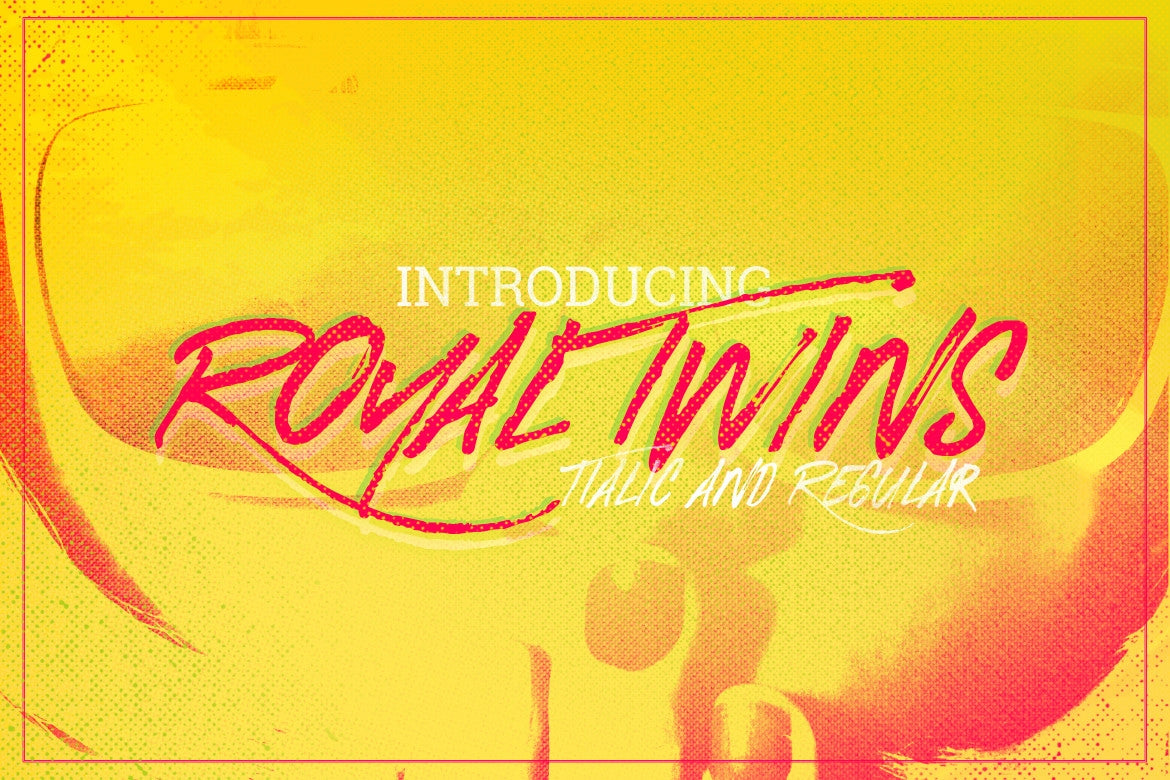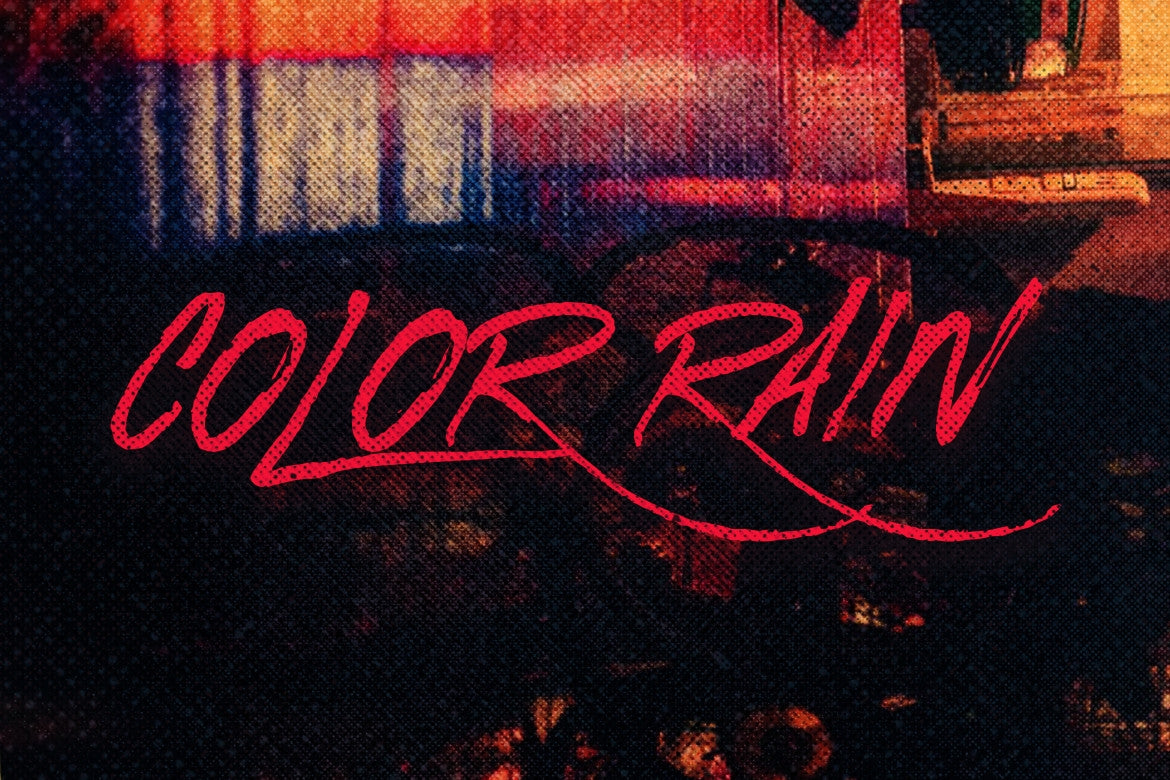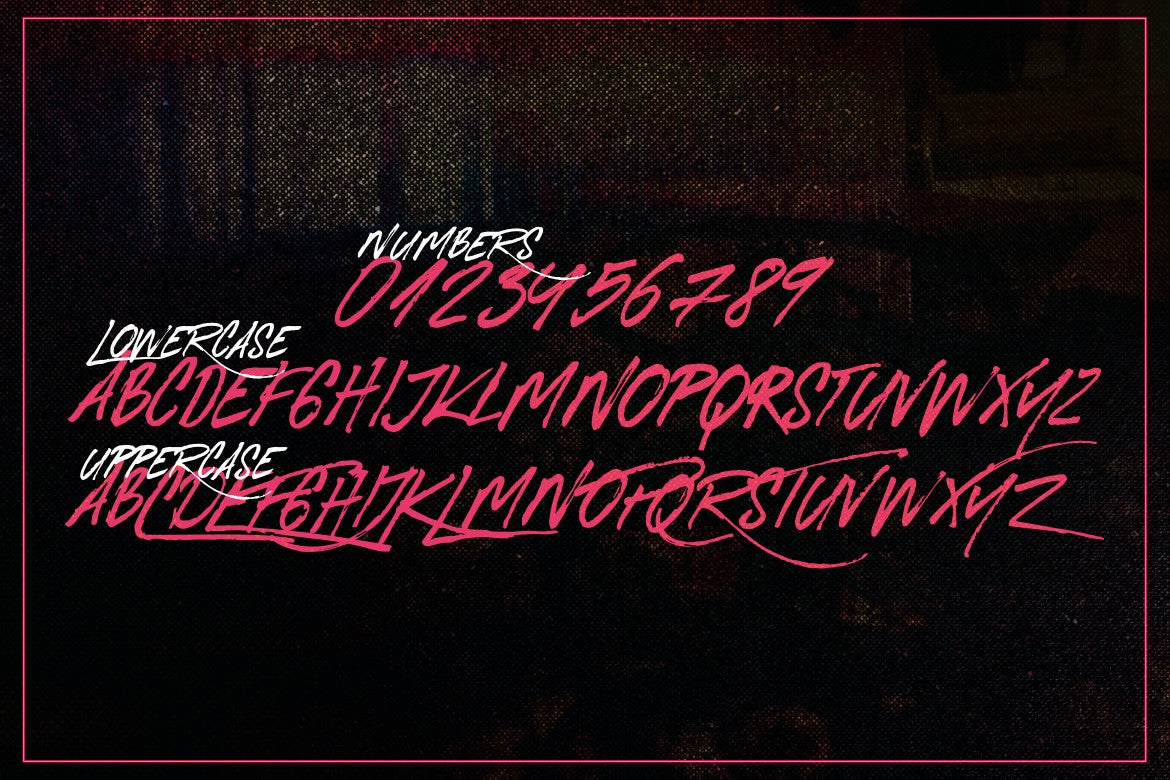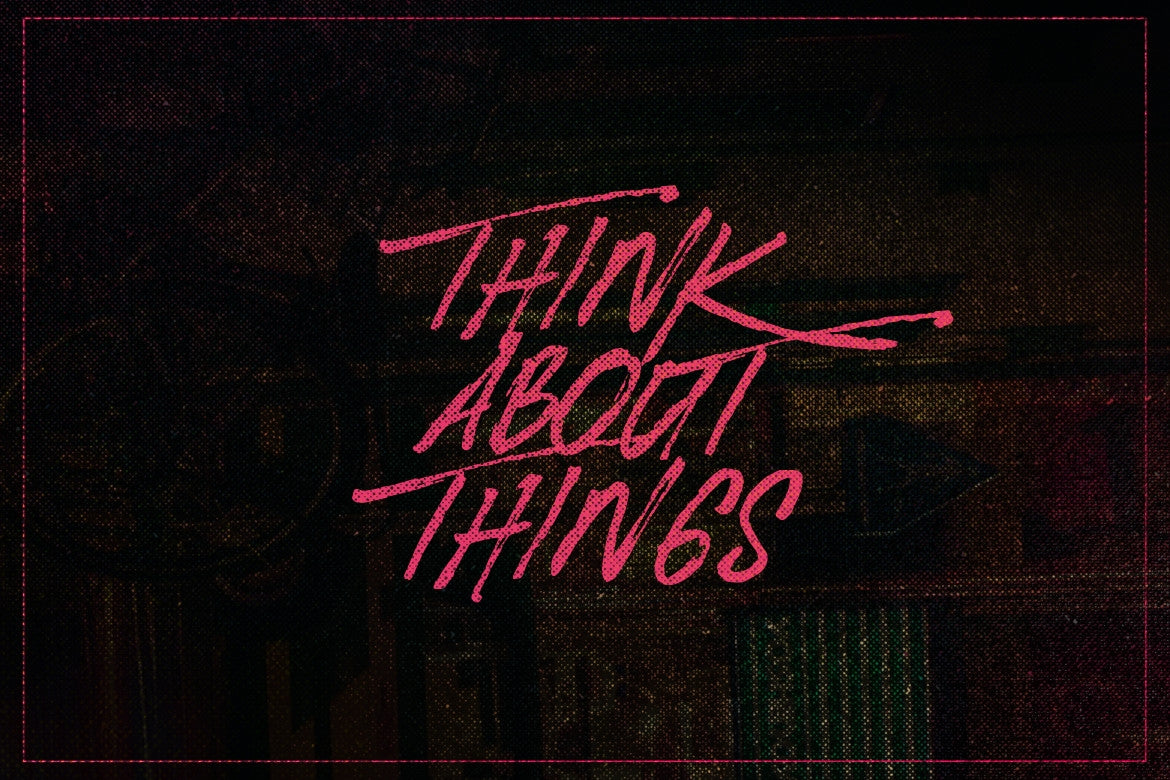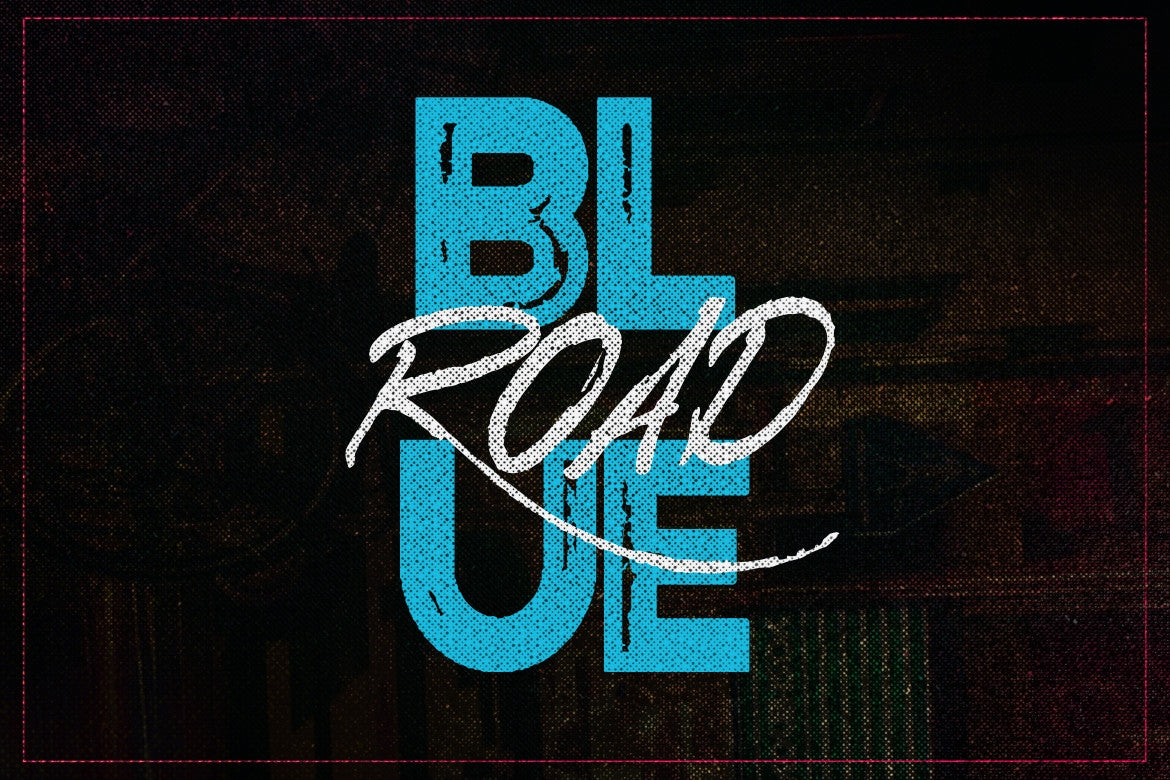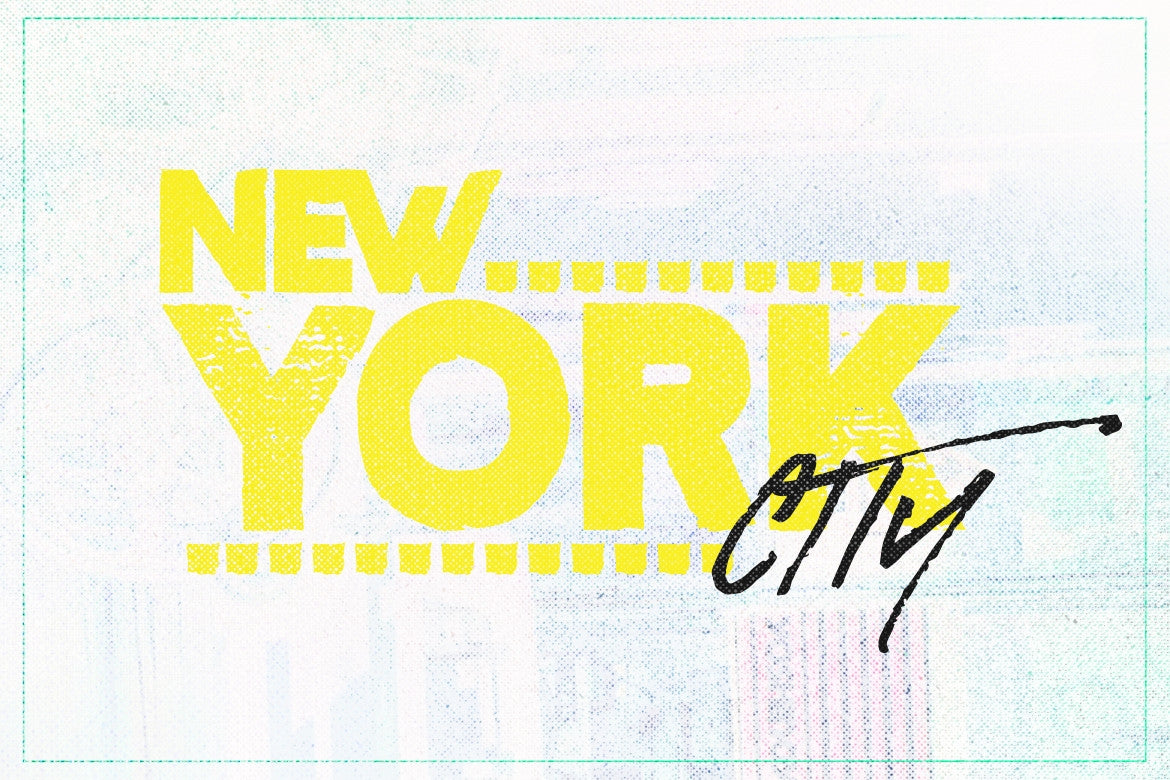
Fuente Royal Twins
La fuente Royal Twins es una fuente de pincel que incluye todos los glifos centroeuropeos y está disponible en versiones regular e inclinada. Una fuente llena de energía, con trazos rápidos y bordes definidos. Ideal para mensajes impactantes. Muy interesante para logotipos, etiquetas de nombre, citas manuscritas, empaques de productos, merchandising, redes sociales y tarjetas de felicitación.
Royal Twins: Fuente con pinceladas manuales que incluye todas las letras mayúsculas, con un conjunto completo de la A a la Z y compatibilidad con todas las letras de Europa Central. Combina mayúsculas y minúsculas para crear estilos de texto interesantes.
RoyalTwins Italic: fuente pincelada a mano con inclinación de 18° que incluye todas las letras mayúsculas, un conjunto completo de la A a la Z y compatibilidad con todas las letras de Europa Central.